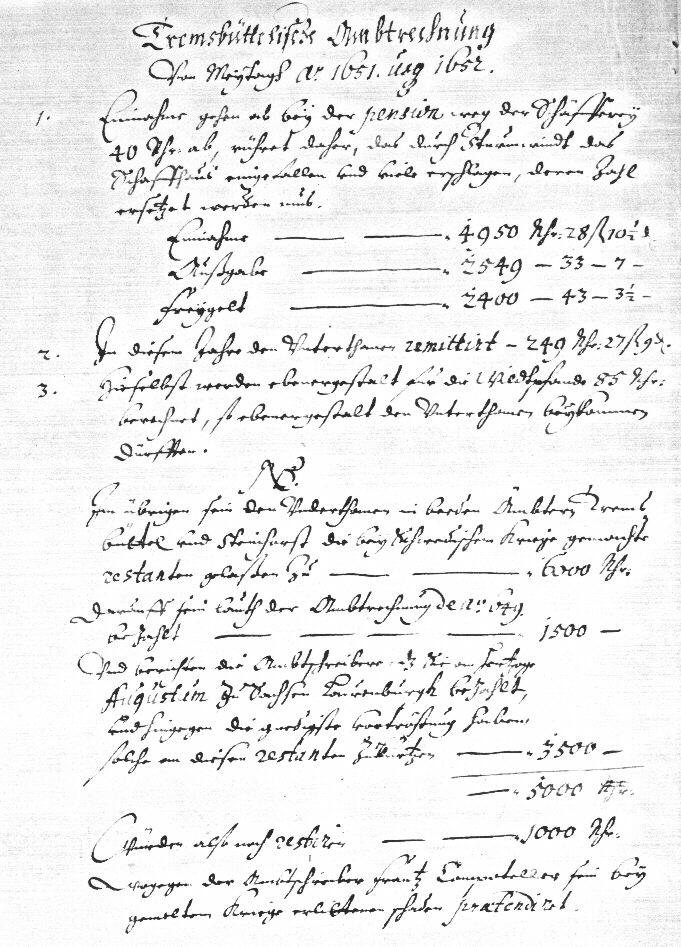
Es handelt sich um eine Kopie, die mir zufällig vorliegt. Leseübungen : eine Amtsrechnung von 1652
An official invoice of 1652
Dies ist das Schlußblatt mit den Endsummen und Anmerkungen.
Lateinische Ausdrücke werden in lateinischer Schrift geschrieben.
Achtung, "v" und "u" sind gleich geschrieben.
Tremsbüttelische Ambtrechnung
Von Meytag Ao. 1651 usq.(= usque) 1652
1. Einnahmen gehen ab bey der pension von der Schäfferey (= Schäferei)
40 Rhr. (Rheichstaler) ab, rühret daher, das durch Sturmwindt das
Schaffhaus eingefallen und viele erschlagen, deren Zahl
ersetzet werden mus.
Einnahme .... 4950 Rhr 28 ß (Schilling) 10 1/2 d (Pfennige)
Außgabe ..... 2549 Rhr. 33 ß 7 d
Freygelt (=Freigeld) .... 2400 Rhr 43 ß 3 1/2 d
2. In diesem Jahr den Unterthanen remittirt - 249 Rhr 27 ß 9 d
3. Hieselbst werden ebenergestalt für die Wiedtpfande (?) 85 Rhr
berechnet, so ebenergestalt den Unterthanen beykommen
dürfften.
NB. (Nota Bene, = Nachsatz)
Im übrigen sein den Underthanen in beiden Ämbtern Trems-
büttel und Steinhorst die bey Schwedischem Kriege (1629) gemachte
restanten gelaßen zu .......... 6000 Rhr.
Darauff sein lauth der Ambtrechnung de Ao. 649 (= 1649)
bezahlet ....... 1500 Rhr.
Und berichten die Ambtschreiber, dz (=daß) Sie vom Hertzoge
Augustin zu Sachsen - Lauenburgk bezahlt,
und hingegen die gnedigste vortröstung haben,
solche an diesen restanten zu kürtzen ..... 3500 Rhr.
(Summe) 5000 Rhr.
Würden also noch restiren (= Rest bleiben) ..... 1000 Rhr.
wogegen der Ambtsschreiber Frantz Compoteller sein bey
gemeltem (= gemeldeten, obengenannten) Kriege erhaltenen Schaden praetendiret(= fordert).